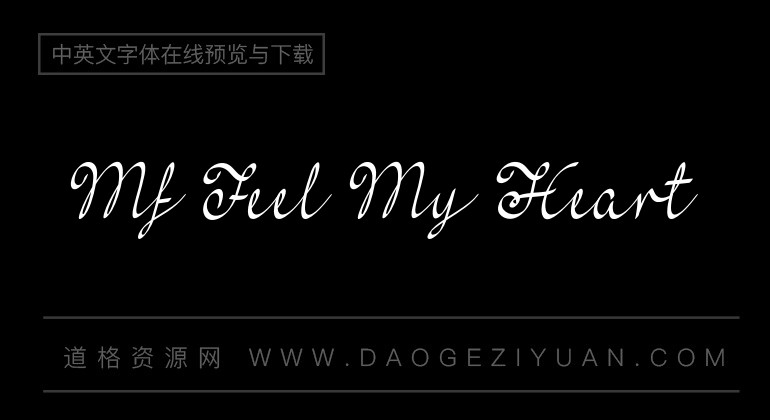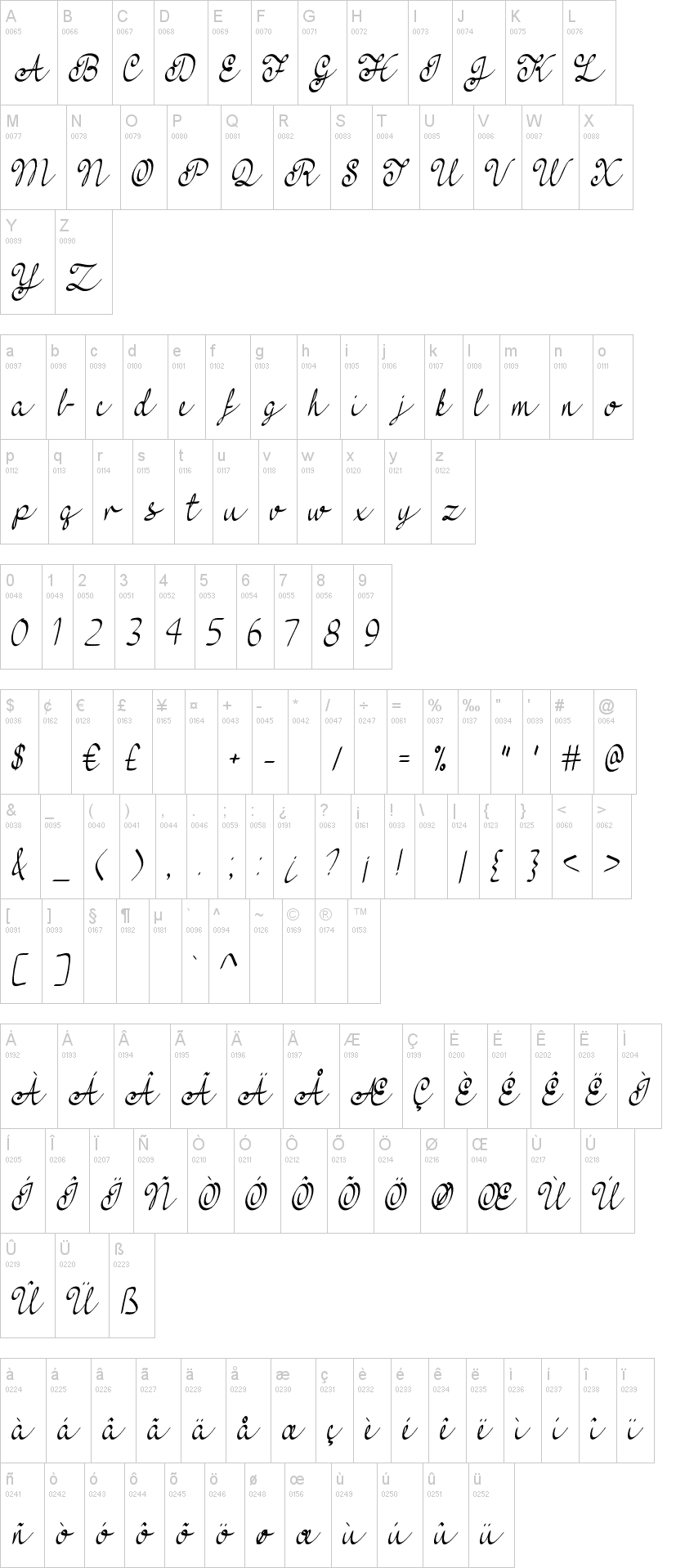
Mf Feel My Heart
Mf Feel My Heart 是一款漂亮的草书字体,由日本设计师Mf创作。这款字体具有流畅的线条,柔和的曲线,以及精致的细节,更能够体现出草书字体的独特魅力。此外,Mf Feel My Heart 字体的字形设计更加精致,让每一个字体都充满着层次感和质感,能够更好地表达出设计师想表达的情感。
Mf Feel My Heart是一款非常不错的手写艺术字体,具有很好的视觉感,适合于文化类的宣传设计、商业类品牌的广告和产品包装设计以及个性化文字排版等较多场景。
Mf Feel My Heart字符映射图